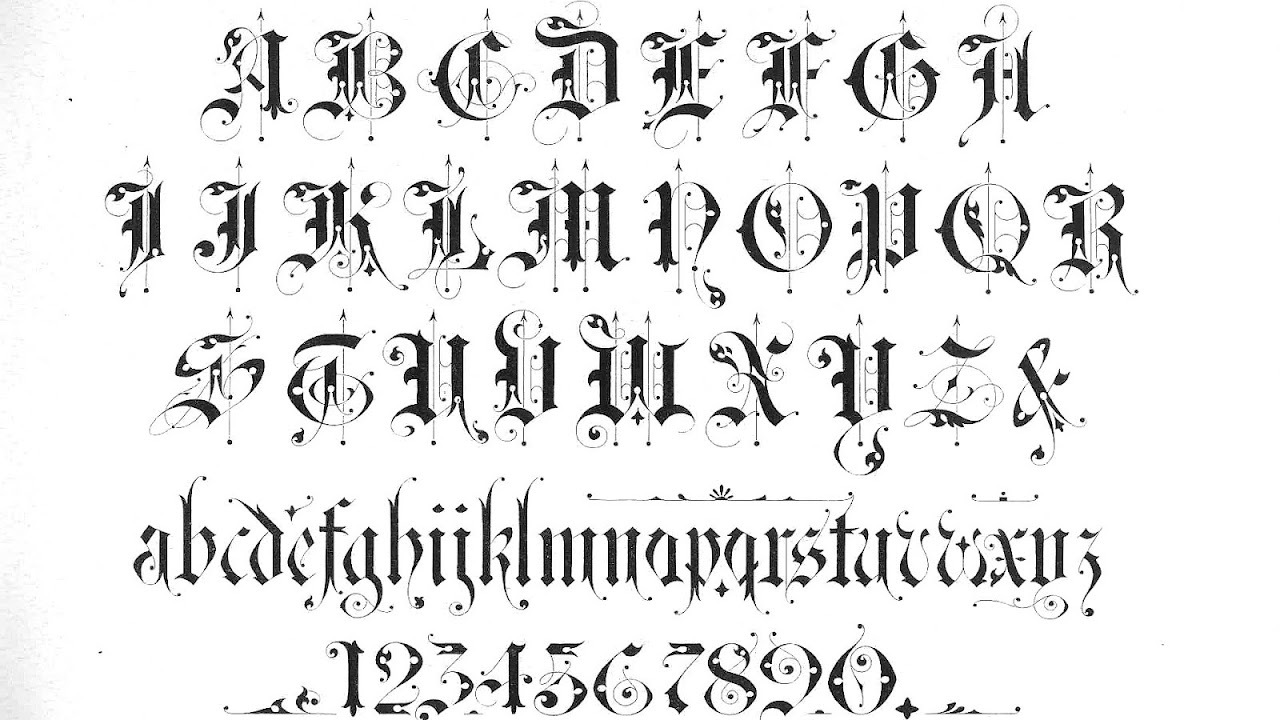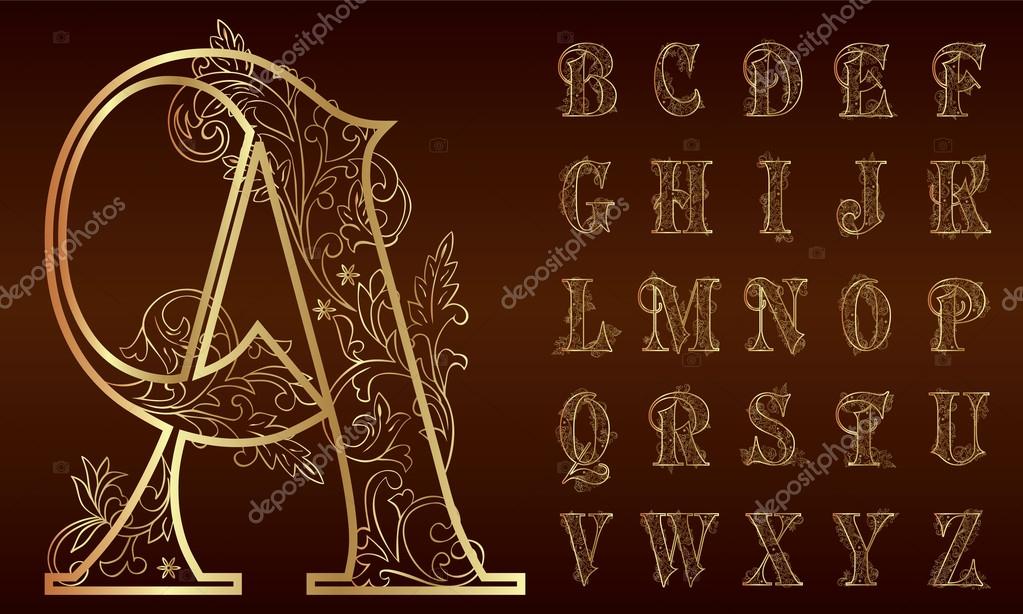
Как сделать надпись на фото красивым шрифтом
Как добавить красивую надпись на фотографию
Добавлять текст на изображение позволяют практически все современные графические редакторы. Однако далеко не в каждой программе это можно сделать действительно красиво. В статье мы предлагаем вам узнать о том, как быстро сделать надпись на фото, которая гармонично впишется в общую композицию снимка и украсит его. Для работы нам понадобится редактор «Студия Эффектов» и буквально 5 минут свободного времени.
Выберите самую лучшую фотографию
Готовы начать работу? Дважды кликните по ярлыку программы и выберите в появившемся стартовом меню опцию «Открыть фото». Найдите на компьютере фотоснимок, который хотите дополнить текстовым комментарием. Выбранная вами фотография моментально появится в рабочей области. Сразу же перейдите в меню «Текст»: именно там вы сможете добавить на фотографию нужную вам надпись и настроить ее.
Добавляйте любые текстовые комментарии
На фотографию тут же будет добавлен текстовый блок. Поменяйте его содержание, указав нужную вам информацию в меню слева. Расположение надписи также можно легко скорректировать.Повернуть надпись можно на шкале «Поворот» в секторе «Дополнительные параметры». Сдвиньте бегунок на линии влево, если хотите повернуть текст по часовой стрелке, вправо — если против нее. Здесь же вы можете скорректировать прозрачность надписи.
Выберите красивый шрифт
Самое интересное в работе с текстом — это подбор шрифта. Кликните по соответствующему раскрывающемуся списку, а затем выделите шрифт, который хотите использовать. Экспериментируйте! Пробуйте разные варианты: правильно подобранные классические, рукописные, готические, контурные и другие виды шрифтов могут стать очень интересным дополнением для фотографии.
Дополните надпись цветным контуром
Итак, вы узнали о том, как добавить надпись на фото и выбрать для нее новый шрифт. Но это далеко не все возможности редактора «Студия Эффектов». Например, дополнительно вы можете настроить стиль начертания текста: сделать его жирным или курсивным, добавить тень, также попробуйте использовать яркий контур.
Выберите эффектную заливку
Украшайте фотографию с помощью рамок и клипарта
Вы смогли сделать надпись на фото красивым шрифтом. Далее сохраните фотографию в любом популярном графическом формате или же попробуйте улучшить её качество. Вернитесь в редакторе фото с эффектами в меню «Эффекты» и подберите в каталоге пресет, который улучшит вашу фотографию. Например, так вы можете стилизовать фото под старинный снимок, повысить его насыщенность, добавить необычный световой эффект… и все это в один клик мыши!
Дополнительно для изображения можно подобрать стильное обрамление. Откройте меню «Рамки» и дважды кликните по приглянувшемуся варианту оформления на панели справа. Аналогично изображение можно украсить яркими картинками («Клипарт»): принцип добавления этих элементов абсолютно идентичен добавлению рамок.
Вот и всё! Вам осталось лишь зафиксировать все внесенные изменения.
Для этого кликните по кнопке «Сохранить». Выберите папку, в которую следует поместить обработанное фото, а затем придумайте название для файла и выберите формат. Теперь вы всегда легко сможете улучшить любое изображение и добавить красивую надпись на фото, если такая необходимость возникнет.
Good Times Regular — бесплатный ретро футуристический шрифт
Good Times — это шрифт заголовков в стиле техно 1980-х годов, вдохновленный буквами, использовавшимися на автомобилях Pontiac примерно 1989–1994 годов.Единые линии веса и отдельные штрихи придают формам букв футуристический вид. Он выпускается в 15 стилях, и его обычный вес доступен для бесплатного скачивания в формате TTF . Разработано Typodermic Fonts.
West Side — 80s Бесплатный шрифт